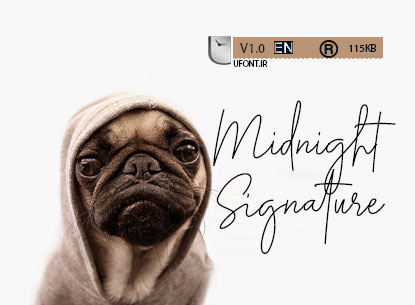
دانلود فونت midnight signature ، فونت دستنویس لاتین سبک لایت مناسب طراحی امضا ، این فونت در بین حروف اتصال دارد و این اتصال بسیار خوش فرم و زیبا اتد زده شده است وبه هیچ وجه تداخلی در بین حروف به واسطه این اتصال ایجاد نمی شود و این یک ویژگی مهم است.
اغلب فونت های دستنویس لاتین به واسطه اتصال بین حروف و عدم یکپارچگی ، در بعضی حروف دچاد نقض ناخوانایی هستند و این موضوع یک ویژگی منفی بسیار بزرگ است که خوشبختانه در فونت midnight signature این مشکل وجود ندارد 🙂